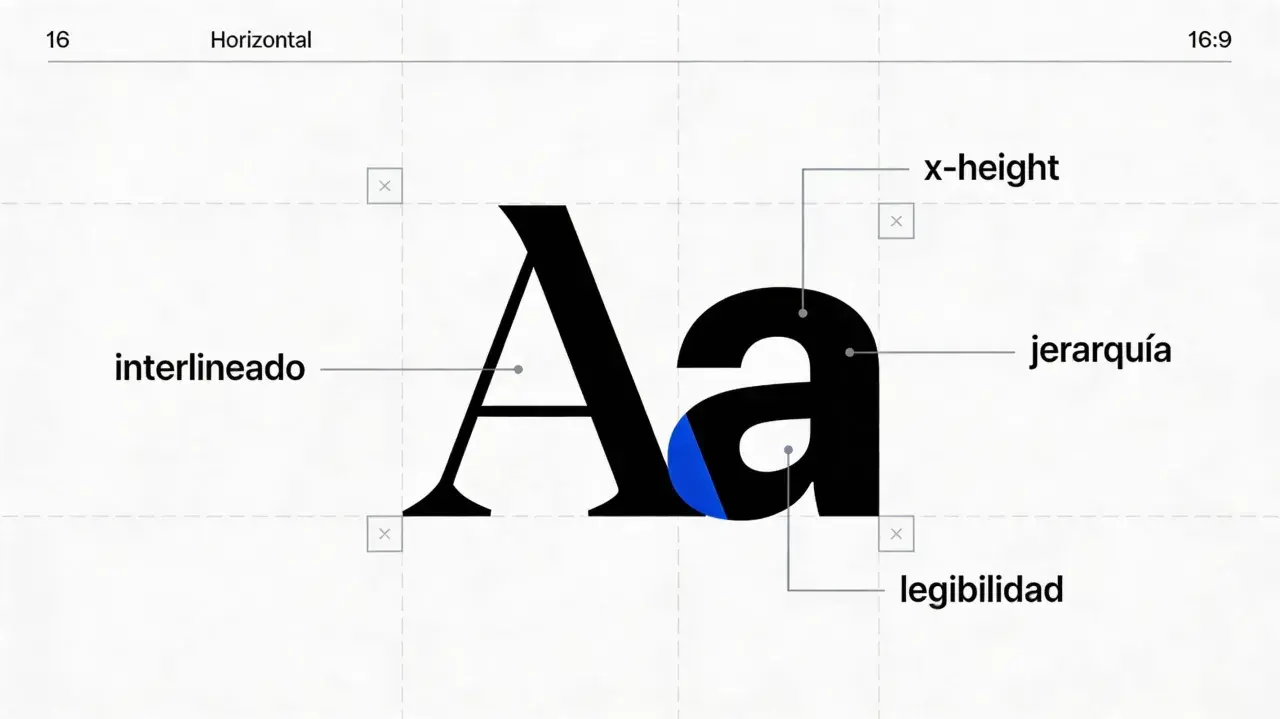
Las letras sueltas funcionan cuando quieres un detalle decorativo con más margen de juego que un rótulo cerrado: sirven para nombres, iniciales, mensajes breves y piezas de manualidades que necesitan presencia sin saturar el espacio. En este artículo te explico cómo elegir material, tamaño y tipografía, qué combinaciones visuales resultan más limpias y qué errores conviene evitar para que el resultado no parezca improvisado.
Lo esencial para elegir y usar letras decorativas sin fallar
- La utilidad cambia mucho según el soporte: pared, balda, mesa o regalo personalizado no piden lo mismo.
- La madera y el MDF son los materiales más versátiles para casa; el acrílico y el metal aportan un acabado más pulido.
- La tipografía define la lectura visual: una serif comunica más peso, una sans serif limpia el conjunto y una script exige más espacio.
- El tamaño importa tanto como el diseño: una pieza pequeña puede perderse si se ve desde lejos.
- Una fijación mal elegida arruina incluso una letra bonita, sobre todo en paredes con textura o en zonas húmedas.
- Si el objetivo es decorar sin sobrecargar, menos color, más coherencia y mejor escala suelen dar mejor resultado.
Qué aporta una letra individual frente a una palabra ya montada
Cuando trabajo una pieza por separado, gano algo que un conjunto cerrado no siempre da: aire. Una letra aislada puede funcionar como inicial, como signo decorativo o como punto de partida para una composición mayor, y eso la hace más versátil en estanterías, paredes pequeñas y regalos personalizados. Además, si el espacio cambia con el tiempo, resulta más fácil recolocar una pieza independiente que rehacer todo el conjunto.
En la práctica, esa flexibilidad se nota en tres usos muy distintos: identificar un nombre, crear una composición más gráfica o dejar que la forma de la letra se convierta en el verdadero objeto decorativo. Esa diferencia importa porque no pides el mismo acabado a una inicial infantil que a un monograma para un recibidor. Con eso claro, el siguiente paso es elegir bien el soporte.
Qué material y acabado encaja mejor con cada uso
Yo suelo empezar por una pregunta muy simple: ¿la pieza va a durar, o solo tiene que lucir bien durante un tiempo concreto? La respuesta cambia por completo el material. Si buscas algo estable para casa, la madera y el MDF suelen ser los más agradecidos; si necesitas ligereza para manualidades o eventos, el cartón pluma o la espuma EVA resuelven rápido; y si quieres un acabado más actual, el acrílico o el metal elevan mucho la presencia visual.
Si la pieza va a una cocina o un baño, yo no me quedaría con un material sin sellar. Y si la idea es moverla de un sitio a otro con frecuencia, elegir algo ligero compensa más que perseguir un acabado demasiado sofisticado. Una vez decidido el material, la tipografía define si la pieza parece artesana, elegante o infantil.
Cómo elegir la tipografía sin perder legibilidad
La forma de la letra manda más de lo que parece. Una serif transmite tradición y un aire editorial; una sans serif limpia encaja mejor en interiores minimalistas; una script aporta gesto manual, pero exige más espacio y suele perder claridad si la haces demasiado pequeña. Yo suelo limitarme a una familia principal y, como mucho, una segunda de apoyo si el conjunto necesita contraste.
- Serif: útil si buscas una pieza más clásica o con presencia editorial.
- Sans serif: la opción más segura cuando quieres limpieza y lectura rápida.
- Script o caligráfica: buena para nombres y regalos, siempre que la escala acompañe.
- Display: funciona en una sola inicial o en piezas muy protagonistas, no tanto en composiciones largas.
En cuanto al tamaño, yo no bajaría de 8 a 12 cm para una balda pequeña y de 20 cm si la pieza se va a leer desde varios pasos. Para composiciones de pared, deja respiración: entre letras, un margen de 1 a 2 cm suele evitar que todo se vea apretado, aunque la proporción final depende del estilo y del soporte. Si una tipografía bonita se lee mal, no ha ganado el diseño; lo ha perdido.
Cuando la escala, el soporte y la forma hablan el mismo idioma, una pieza pequeña se convierte en un acierto muy visible. Y ahí está, al final, la diferencia entre un adorno cualquiera y una letra que de verdad ordena el espacio.